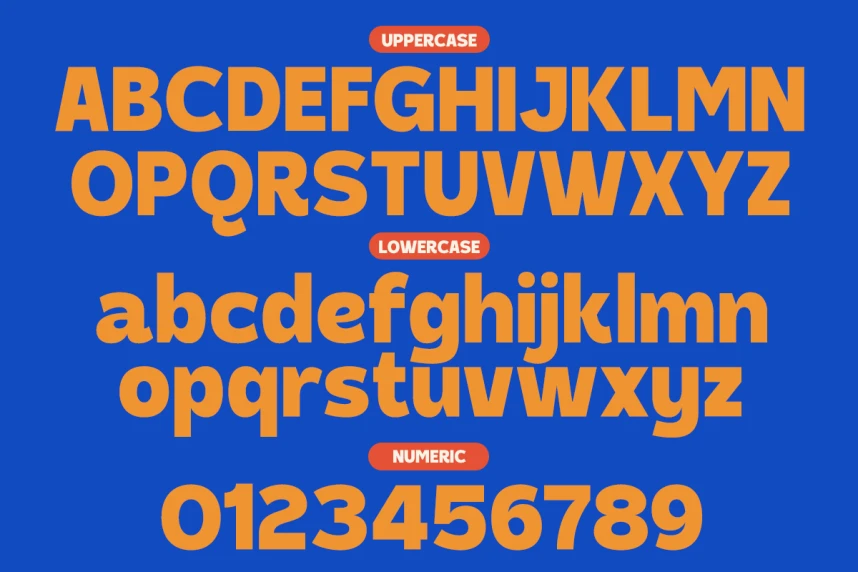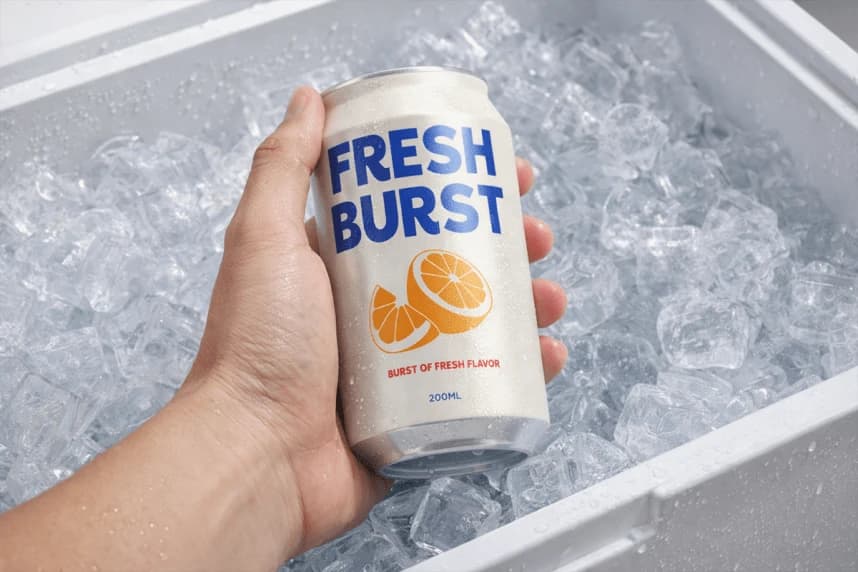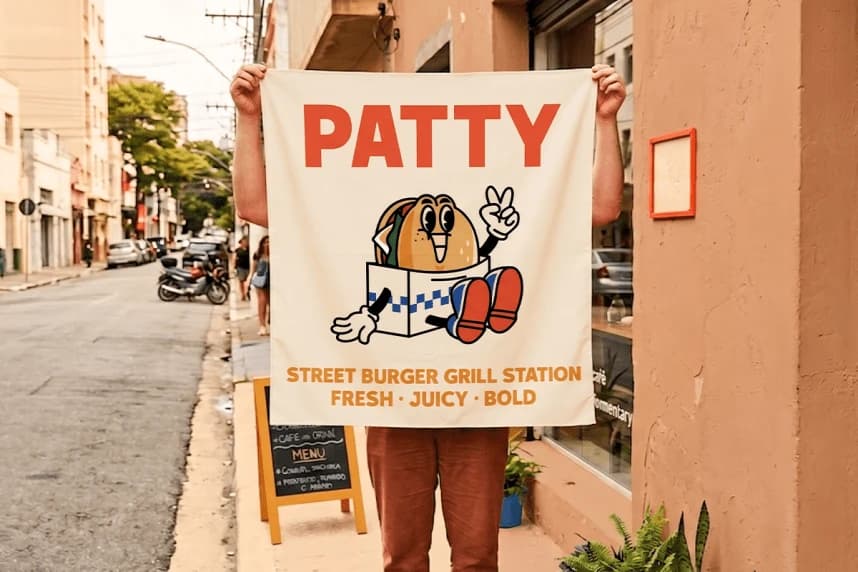
Patugo DEMO Font, yaratıcı projelerinize enerji, eğlence ve güçlü görsel etki katması için tasarlanmış cesur bir sans display yazı tipidir. Kalın hatlı harf biçimleri ve akıcı eğrileriyle Patugo, anında dikkat çeken, oyunbaz fakat kendinden emin bir kişilik sunar. Kalın yapısı maksimum okunabilirlik
Patugo DEMO Font, yaratıcı projelerinize enerji, eğlence ve güçlü bir görsel etki katması için tasarlanmış cesur bir sans display yazı tipidir. Kalın hatlı harf yapıları ve yumuşak eğrileriyle Patugo, anında dikkat çeken oyunbaz fakat kendinden emin bir karakter sunar. Kalın yapısı, benzersiz ve samimi bir karakteri korurken maksimum okunabilirliği sağlar.